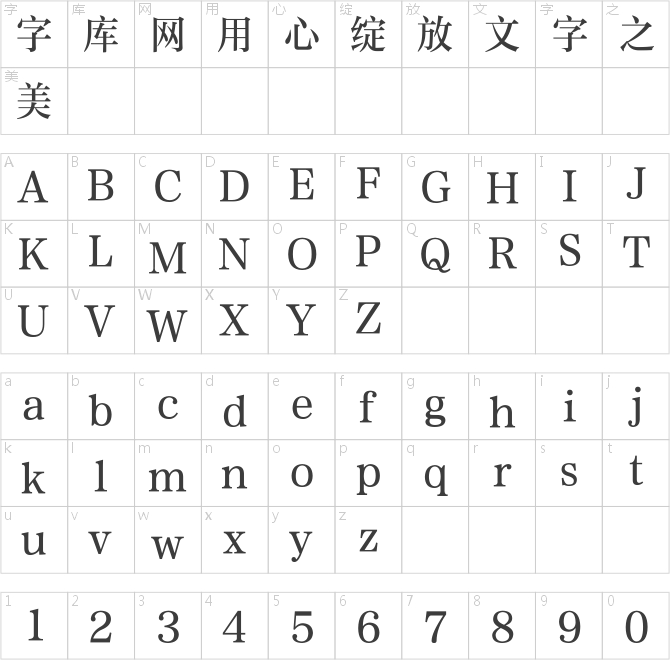
凱迪拉克方正準(zhǔn)雅宋簡(jiǎn)體 詳情頁(yè)
宋體
凱迪拉克方正準(zhǔn)雅宋簡(jiǎn)體字體字庫(kù)是一款讓人賞心悅目、百看不厭的中文字體,適合各類廣告和產(chǎn)品包裝設(shè)計(jì)應(yīng)用,字體大小2.47MB,格式為TTF字體,上傳用戶是華大文化傳媒,作者/版權(quán)方為方正字庫(kù)